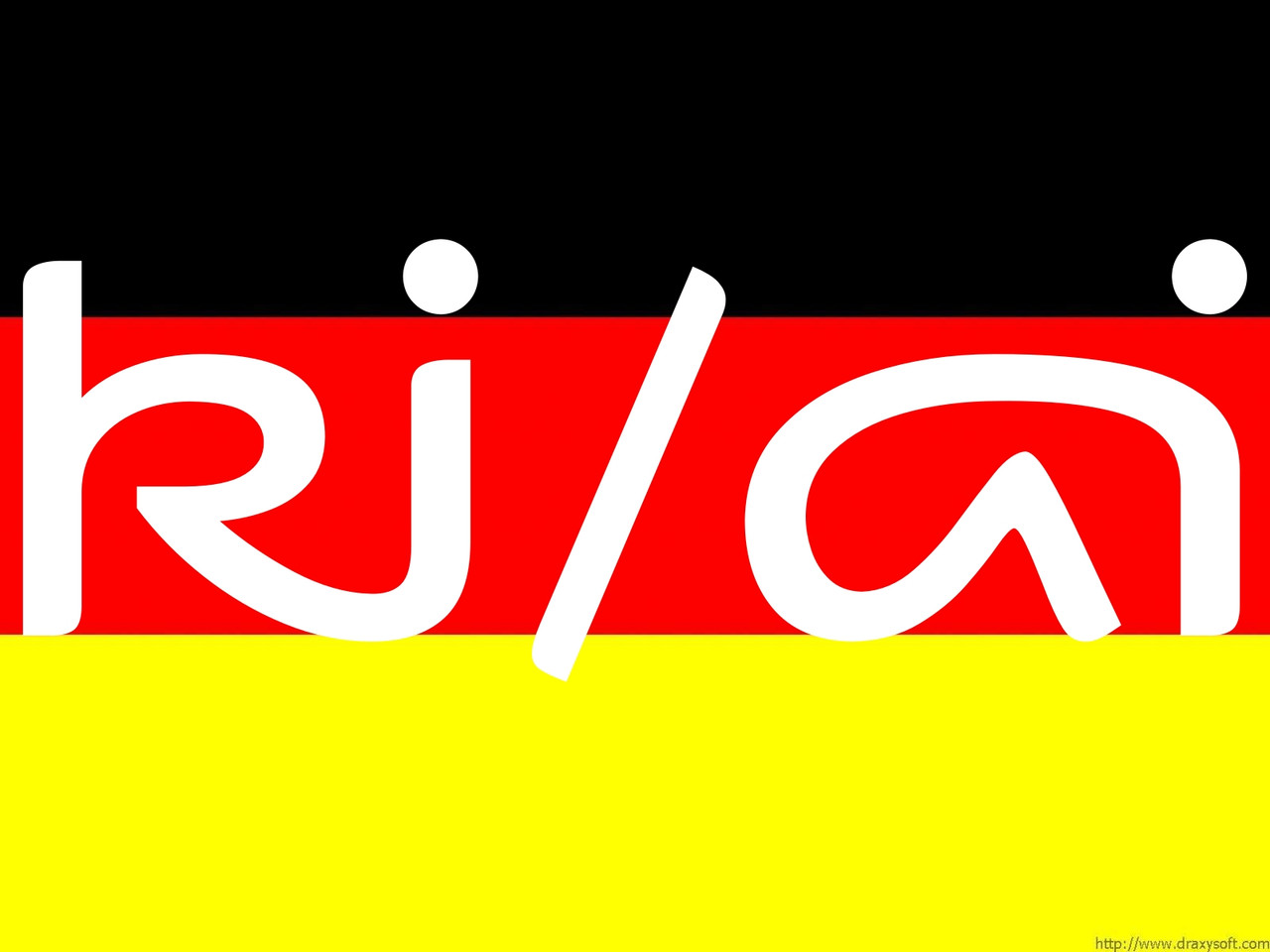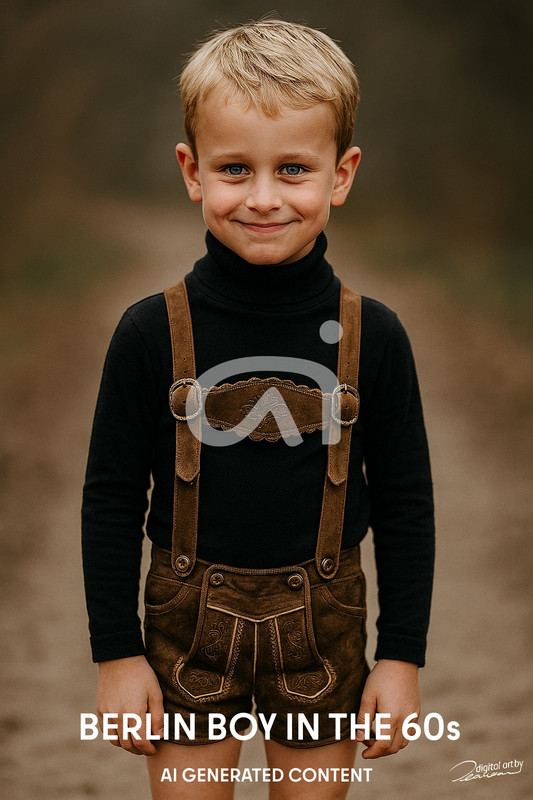
AI Ligatur für KI inhalt sinnvoll!
ich wollte einmal fragen, ob es Sinn macht, das Thema AI/KI in der Typografie zu thematisieren.
Jeder weiß inzwischen, dass in der EU KI‑generierte Inhalte gekennzeichnet werden müssen. Da stellt sich die Frage: Warum nicht auch typografisch sichtbar machen?
👉 Meine Idee: Aus dem „@“ ein AI‑Zeichen zu entwickeln – ähnlich einer Ligatur. Wenn man sich manche Fonts anschaut, sieht man, wie viel Mühe Designer in die Gestaltung des @‑Symbols gesteckt haben. Warum also nicht auch für „AI“ ein eigenständiges typografisches Zeichen schaffen?
🎨 Beispiele & Argumente für Typografen
Ligatur‑Tradition: Schon seit Jahrhunderten gibt es Ligaturen wie „æ“, „œ“ oder „ß“. Sie entstanden aus praktischen und kulturellen Gründen. „AI“ könnte die nächste logische Erweiterung sein.
Kennzeichnungspflicht: Da KI‑Inhalte künftig markiert werden müssen, wäre ein typografisches Symbol eine elegante Lösung – klar, sichtbar und konsistent.
Gestalterische Freiheit: Ein „AI“-Ligaturzeichen könnte in Serif‑Fonts ornamental wirken, in Sans‑Serif minimalistisch. So wie das @‑Zeichen je nach Schriftart unterschiedlich interpretiert wird.
Vergleich mit @: Das @ war ursprünglich ein kaufmännisches Zeichen, das durch E‑Mail global Bedeutung bekam. „AI“ könnte eine ähnliche typografische Karriere machen – vom Fachzeichen zum Alltagszeichen.
Praktische Anwendung:
In wissenschaftlichen Texten: Kennzeichnung von KI‑Abschnitten.
In Corporate Design: Firmen könnten KI‑Inhalte mit einem eigenen „AI“-Glyph branden.
In Interfaces: Ein Symbol für „AI‑generiert“ wäre schneller erkennbar als ein ausgeschriebener Hinweis.
📌 Fazit
Die Diskussion lohnt sich: Sollten wir als Typografen ein neues Zeichen für „AI“ entwickeln – vielleicht als Ligatur, vielleicht als eigenständiges Symbol? Es wäre eine Chance, die Schriftkultur aktiv mitzugestalten und auf aktuelle gesellschaftliche Entwicklungen zu reagieren.
Jeder weiß inzwischen, dass in der EU KI‑generierte Inhalte gekennzeichnet werden müssen.
Das ist per se falsch.
In manchen Fällen müssen Texte und Bilder gekennzeichnet werden, die stellen in der Praxis aber die Ausnahme dar. In Kürze:
Text:
KI-generierter Text muss nur dann gekennzeichnet werden, wenn er ungeprüft veröffentlicht wird.
Bei einer redaktionellen Überarbeitung und bei einer menschlichen Kontrolle entfällt die Kennzeichnungspflicht.
Bild:
Es gibt in D keine allgemeine gesetzliche Pflicht zur Kennzeichnung KI-generierter Bilder.
Es gibt aber Anwendungsfälle, in den KI-generierte Bilder gekennzeichnet werden müssen, beispielsweise bei Deepfakes. Diese können auch schnell mal – wenn bestimmte Personen dargestellt sind – gegen das Recht am eigenen Bild, das allgemeine Persönlichkeitsrecht oder das Urheberrecht verstoßen.
Eine Kennzeichnungspflicht kann sich auch durch redaktionelle Vorgaben von Medienhäusern oder Plattformen ergeben. Auch die Lizenzbedingungen des KI-Anbieters können eine Kennzeichnung vorschreiben. Diese basieren aber auf keiner gesetzlichen Grundlage.
Ein weiter Weg wäre das ...
Das @ gabs ja schon lange, das ist/war kein neues Zeichen.
Das neue Zeichen noch nicht, außer wir finden was altes was kaum mehr in Gebrauch ist, aber passt.
Also erst mal eine Form finden ...
Dann das Zeichen rechtssicher als gültige Kennzeichnung etablieren ...
Dann einen Unicode beantragen (der aber eher nur dokumentiert, was existiert?) ...
Dann in (möglichst allen) Schriften implementieren ...
Dann die (verpflichteten) Anwender davon überzeugen das Zeichen zu verwenden statt anders zu kennzeichnen ...
Ein Schriftzeichen hätte gegenüber einem Logo immerhin den Vorteil, dass es als Unicode mit dem Text gespeichert werden kann, nicht irgendwie beigestellt werden muss. Also ja, grundsätzlich nicht sooo verkehrt. Nur mühsam.
Wäre bei der allgegenwärtigen K»I« nicht ein Zeichen für »handgemacht/geistgedacht« sinnvoller? Davon könnte beispielsweise dann auch das Handwerk profitieren wie Bäcker*innen, die noch backen und nicht nur industrielle Rohlinge aufbacken,
vor 10 Stunden schrieb Diwarnai:
"Das ist per se falsch...."
EU‑KI‑Gesetz (Verordnung (EU) 2024/1689, „AI Act“) geregelt. Der maßgebliche Artikel ist Artikel 50.
📜 Juristischer Originalkern (Artikel 50)
Anbieter müssen sicherstellen, dass Menschen wissen, wenn sie mit einem KI‑System interagieren.
KI‑Systeme, die Inhalte erzeugen oder verändern (Texte, Bilder, Audio, Video), müssen diese Inhalte klar als KI‑generiert oder KI‑bearbeitet kennzeichnen.
Für synthetische Audio‑, Bild‑ oder Videoinhalte („Deepfakes“) gilt eine verbindliche Kennzeichnungspflicht, außer wenn es offensichtlich ist, dass es sich um Kunst, Satire oder Ähnliches handelt.
Wie soll ein einzelnes Zeichen an Bild, Text, Layout, Code usw, dieses als KI-generiert kennzeichnen? Wenn das nicht möglich ist, braucht es auch ein solches Zeichen nicht.
Naja, ein wie auch immer geartetes »Label« könnte ja auch aus einer Ligatur gestaltet sein. Aber ich denke mittlerweile hat sich schon etwas anderes etabliert: der vierzackige Stern (Google nutzt diesen bereits zur Kennzeichnung bei seinen KI-generierten Bildern). Auch dieser ließe sich ja spielend leicht in Fonts integrieren, wenn nicht schon vorhanden.